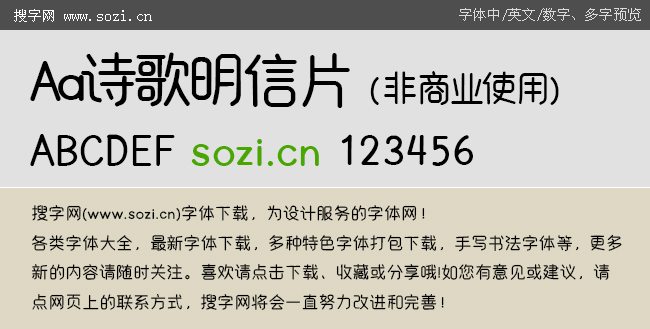
Aa詩歌明信片
搜字網給大家提供一款Aa詩歌明信片(非商業(yè)使用)中文字體下載,Aa詩歌明信片是一款藝術字體,字體線條粗細適中,筆畫隨性,結構肆意灑脫,具有很好的視覺感。適合應用于藝術設計、平面宣傳設計、網頁設計、海報設計等應用(此字體為個人非商用版,商用可以聯(lián)系QQ:1006760504)。